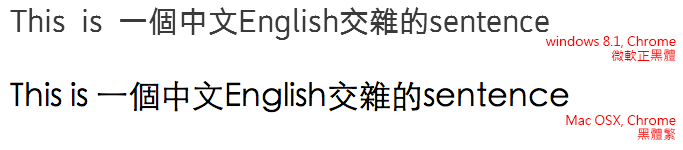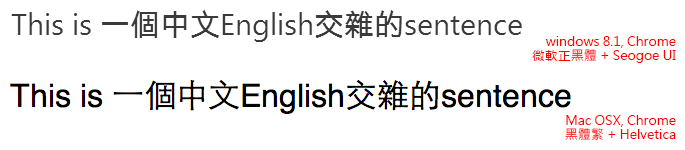
CSS設定中英文不同的字體
Just font中的字型學文章都相當有意思,而有一篇是關於中英文字搭配的問題;這篇雖然是以windows word為例,但裡面的概念在網頁上也是很有幫助,而其中一段”以 Windows 內建的三種字型為例,表現最好的是微軟正黑體,英文部分採用了微軟的 Segoe UI,粗細與中文較一致“,在目前web中當然也可以有這樣的設定,只要用CSS3的unicode-range,就能夠在中文字中套用”微軟正黑體”,英文套用”Segoe UI”。
本篇重點
了解unicode-range的使用方法。
效果展示
unicode-range部分效果在Mac OS上測試有問題,不管是Chrome、Safari、Firefox都有點問題…。
這一句話只有"我"會被換成黑體
以上面這一段文字為例,在windows內,”我”這一個文字會被替換成微軟正黑體,而其他文字沒有變化。
如果參考Mozilla 的MDN可以了解到,
再參考uni code的表,可以查詢各文字的unicode。
用這樣的方式就能夠選取特定的文字,或是語系等等。
針對指定語系設定
在一般來說,通常換字體沒有針對語系,就像下方這一個範例,我將字體換成了’Mac OS 黑體-繁’、’Windows 微軟正黑體’,但在中英文排版中,用同一種字體不一定合適(請看just font)。
中文的語系的unicode-range為U+4E00-9FFF,英語系為U+00-024F,將這個值加入到@font-face內,就能為特定語系換字體。如下範例中文還是’Mac OS 黑體-繁’、’Windows 微軟正黑體’,但英文的部份已經替換成’Helvetica’、’Segoe UI’,範例如下。
在css內只要將兩者的font-family皆設定相同名稱,但指向不同的unicode-range,就可以達到這樣的效果。
其他範例
不只在黑體能夠這樣做,明體當然也可以。
延伸發現
在字符百科中,不僅可以查詢的文字的unicode 編號,其實還可以查到許多符號性的文字,這些文字其實可以直接當作web font使用,還免載入外部的字型檔,就像下方的幾個不同雪花一樣。